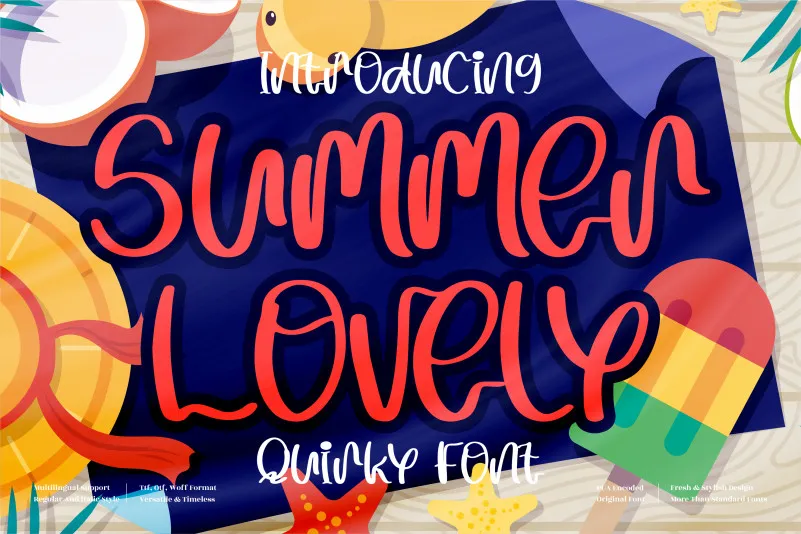
Summer Lovely Font – Download Grátis
Esta é uma fonte cursiva cheia de personalidade, projetada para adicionar um toque único a qualquer projeto que precise de beleza leve e descomplicada. Perfeita para aplicações como designs relacionados à cartoon, jogos infantis, citações, títulos, nomes de marcas, capas de livros ou até mesmo postais, este é um ótimo escolha. Com uma mistura de graça e fantasia, Summer Lovely Font se torna a fonte ideal para quem busca uma forma fresca e divertida que se adaptará perfeitamente à sua necessidade criativa. Aproveite esse recurso visual moderno e encoraje seus projetos a brilharem ainda mais com essa elegante, mas descontraída fonte.